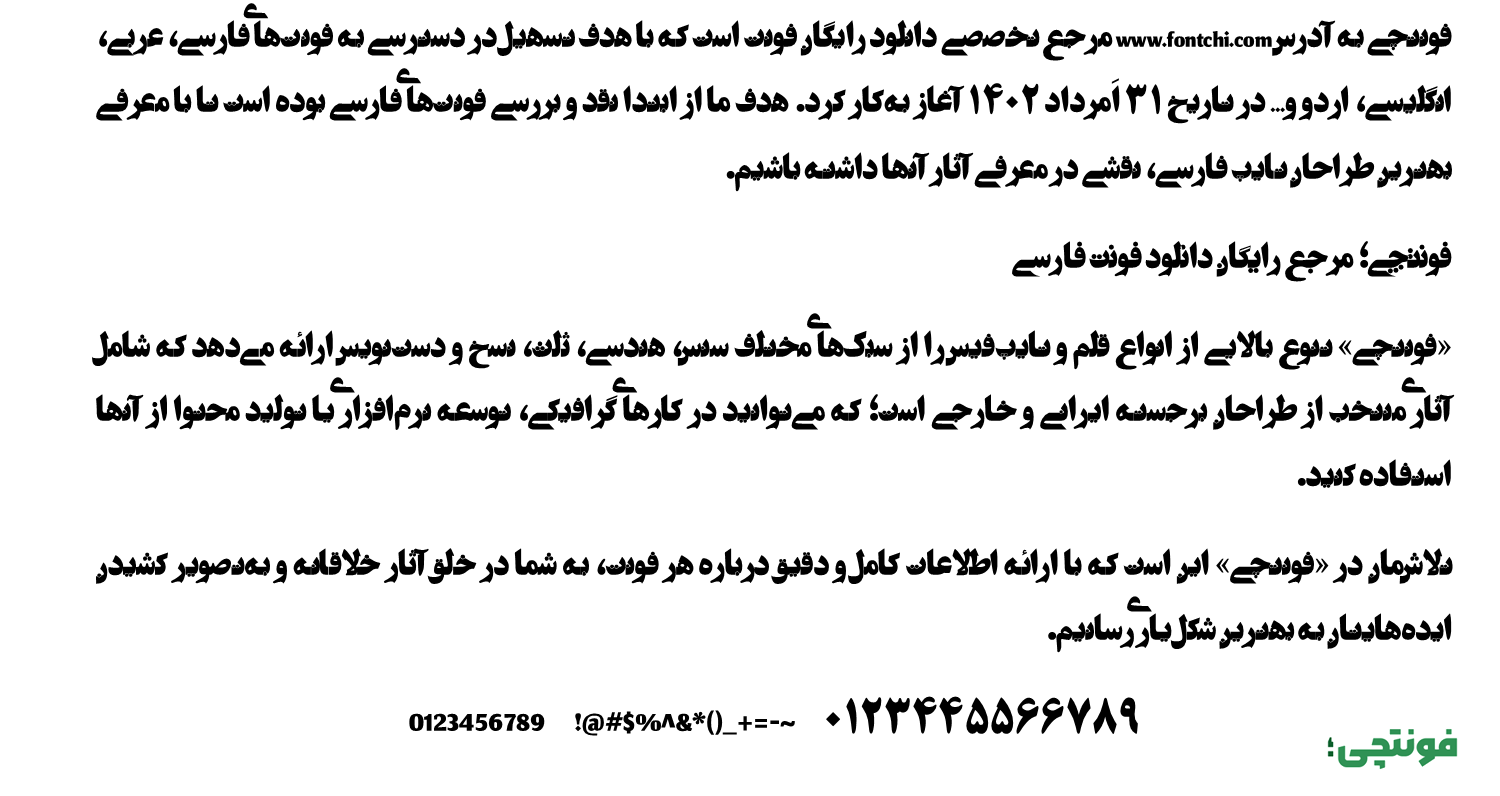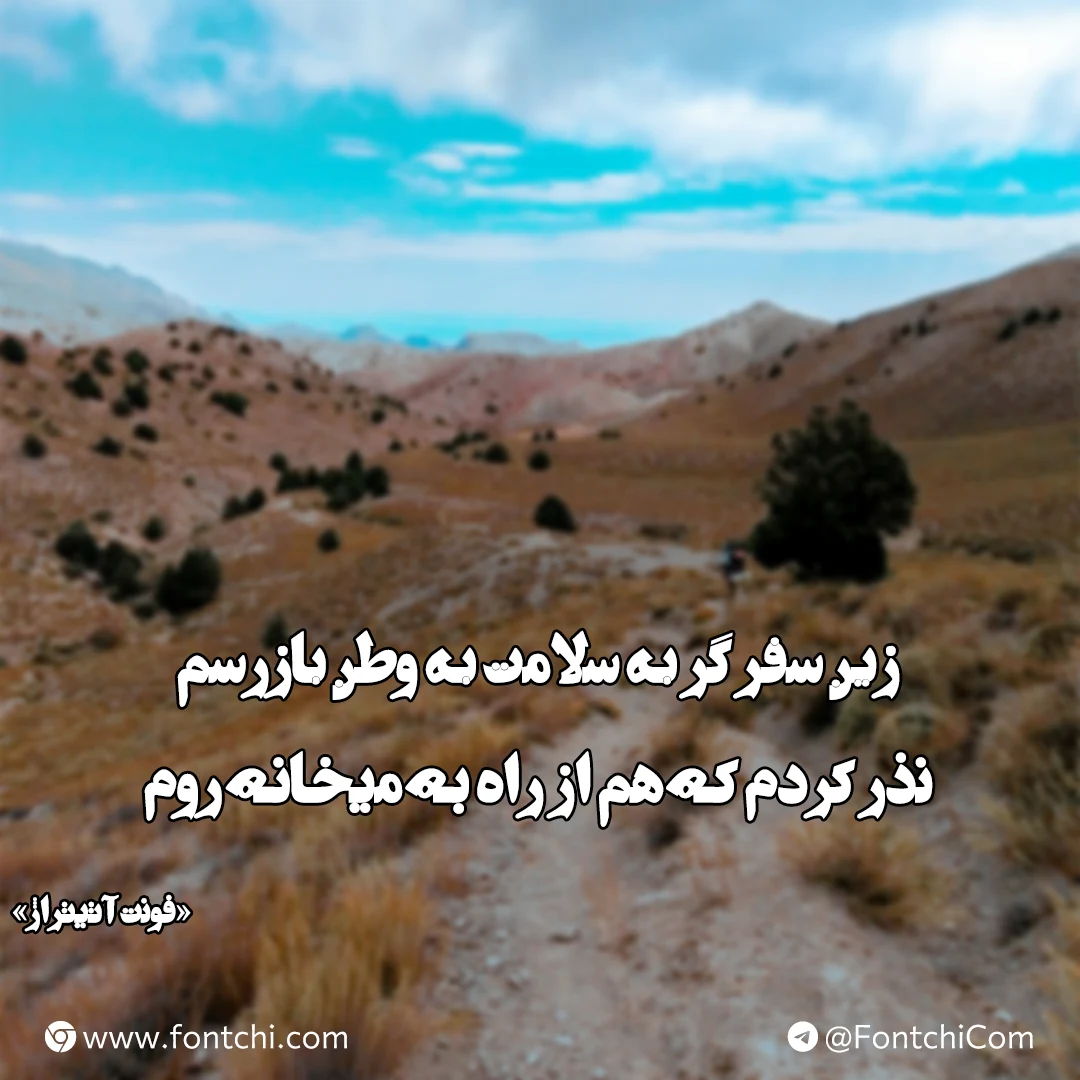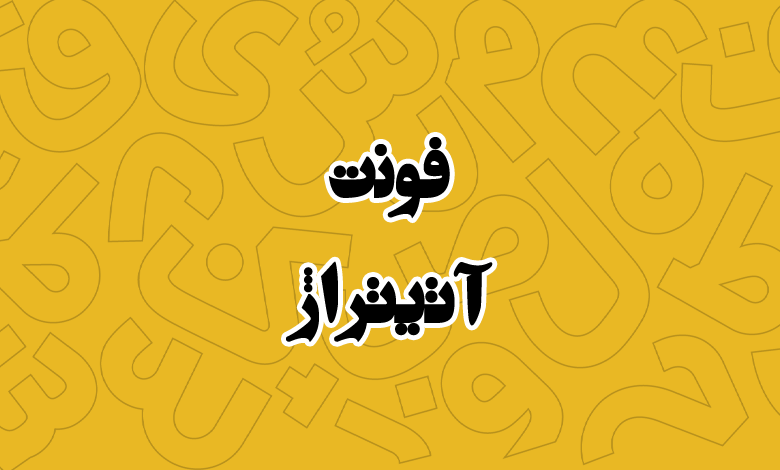
فونت تیتراژ (A Titraj)
فونت تیتراژ یا آ تیتراژ (به انگلیسی: A Titraj) از سری فونتهای رایگان با سبک فانتزی و سنس است که ظاهری بولد و سیاه دارد. از این فونت میتوانید در متون کوتاه و عناوین استفاده کنید که با ظاهر نمایشی خود، نگاه مخاطب را به خود جلب میکند.
این فونت زیبا از سری فونتهای پرشین است که توسط امیرحسین صدقی طراحی شده است. نقطههای این فونت به شکل خاصی در اطراف یا درون حروف جایگذاری شده است که نمونه آن را در تصویر زیر مشاهده میکنید.
در فونت تیتراژ سری ۱ نقاط درون حروف جای گرفته است. گویی که نقطهها را در آغوش گرفته باشند. همین امر موجب شده تا این فونت ظاهری فانتزی داشته باشد. اما در سری ۲ نقطهها از این ساختار خارج شده و در مقابل روی فانتزی کردن حروفی مانند «ه، ر، ی، ن» تمرکز شده است که با ظاهر متفاوت و ایجاد تناقض، خودنمایی کنند.
فونت آ تیتراژ از زبان فارسی پشتیبانی میکند و ساختارهای خاص زبان عربی را نیز در خود دارد. تنها کاستی آن در بخش اعداد است که برای اعداد «۰۴۵۶» هم از اعداد عربی استفاده شده است.
حروف انگلیسی در این فونت دارای گلیف اختصاصی نبوده و از فونت سیستم عامل برای آنها استفاده میشود که در این صورت باید از یک فونت جایگزین انگلیسی استفاده کنید.
فونت تیتراژ همانطور که گفته شد برای متون کوتاه و عناوین مناسب است. از کاربردهای این قلم میتوان به موارد زیر اشاره کرد:
- فونت تامنیل و پست در شبکههای اجتماعی.
- فونت عناوین کتاب و مجلات خصوصا برای موضوعات داستانی یا فانتزی.
- استفاده در صنایع چاپ همچون بنر و بیلبوردهای تبلیغاتی با ابعاد بزرگ که نیاز به جلب توجه دارند.
- فونت اسلایدر تصاویر در سایت که با جلی توجه کاربران را به صفحات مهمی مانند دستهبندی محصولات هدایت کند.